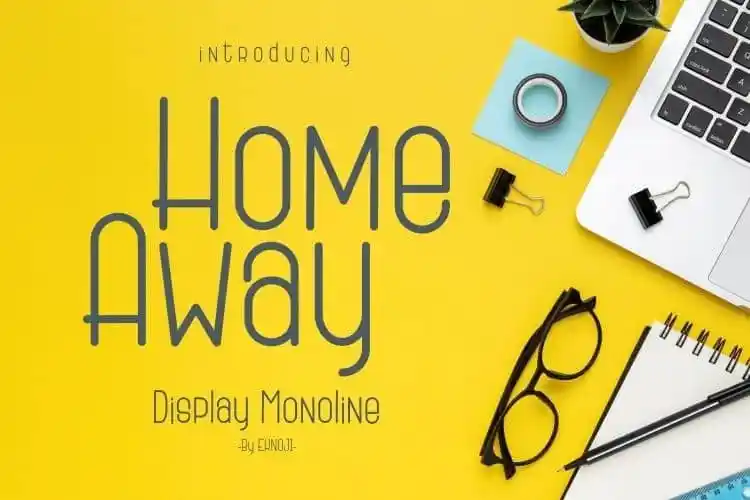
Home Away Display Font – Fonte Grátis
Home Away Display Font
A Home Away Display Font é uma fonte moderna e fashion, cuidadosamente criada pela Eknoji. Cada letra foi meticulosamente desenhada para que suas mensagens fiquem um pouco mais únicas e atraentes. Esta fonte é perfeita para incorporar em diversos tipos de projetos, desde selos e identidades visuais até postagem de mídia social, publicidade, embalagens de produtos, etiquetas ou mesmo marcas especiais. Não importa qual seja o seu projeto, Hantoria Signature tem a habilidade de transformá-lo em algo realmente especial e agradável aos olhos.